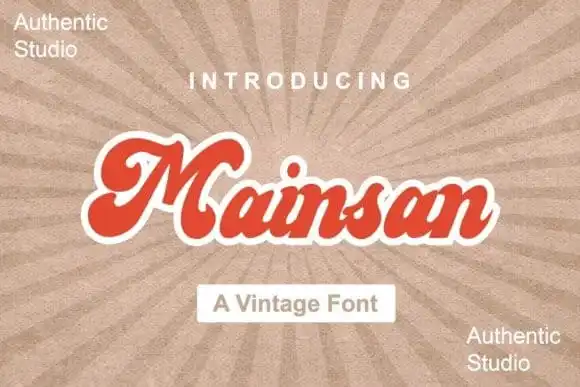
A Mainsan Script Font é uma escolha ideal para quem busca um visual retrô natural no design gráfico. Esta tipografia feita a mão apresenta um estilo limpo e autêntico, sem falsas promessas de sofisticação excessiva. As linhas suaves e os traços naturais conferem à Mainsan uma identidade única que parece convidar a memórias da era dos discos vinil e câmeras analógicas. Esta fonte é perfeita para aqueles projetos de design que buscam uma sensação nostálgica, seja quando se trata de adicionar um toque retro a capas de álbum, cartões de visita ou até mesmo o bordado em um retrato digital. Suavemente atemporal e versátil, ela permite ao designer explorar suas capacidades criativas sem sacrificar a estética cuidadosa do passado. Em cada projeto que escolher aplicar Mainsan Script Font, você adicionará aquele toque especial de nostalgia à sua ideia original.